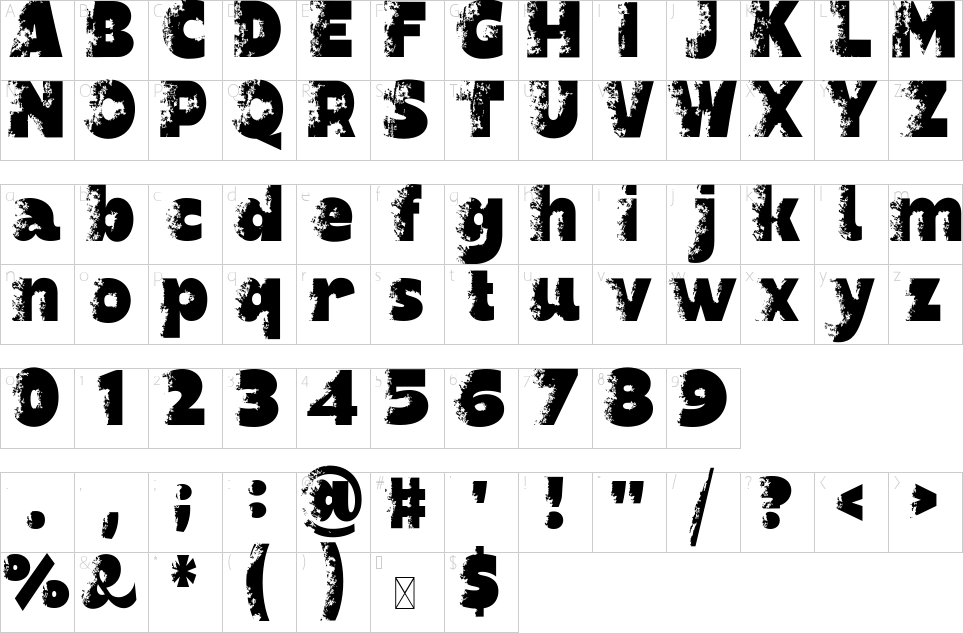
Grunge Font – 1001 Free Fonts – Fonte Grátis
Aqui está uma descrição em português do Brasil, envolvente e natural para a página de download da fonte ‘Grunge Font – 1001 Free Fonts’: Descubra a fonte Grunge disponível gratuitamente e facilmente instalável tanto no Windows quanto no Mac. Com seu design criativo e inovador, a Grunge font se destaca em ambientes onde um estilo arredondado e desorganizado é procurado. O designer 177Studio.com trouxe esta fonte com uma variedade de estilos para enriquecer qualquer projeto visual. Se você está buscando dar um toque único à sua arte digital ou layout web, a Grunge font pode ser a solução perfeita. Sujeitada ao movimento grunge dos anos 90 e suas referências artísticas, esta font oferece um ar de irreverência que certamente vai chamar atenção. Combinando linhas robustas com detalhes suaves e desorganizados, é uma ótima escolha para aqueles que buscam dar ao seu design uma pegada única e autêntica. E melhor ainda: esta fonte está disponível gratuitamente para download em sua versão de 1001 Free Fonts. Se você precisa criar um layout minimalista ou temprece com um estilo mais arrumado, a Grunge font não é apenas útil, ela também oferece uma maneira única de diferenciar seus projetos. Seja para aplicativos móveis ou sites web, a escolha desta fonte pode transformar sua produção em algo que destaca-se do resto da multidão. Portanto, se você está procurando por um pouco de diversidade e criatividade na sua próxima peça gráfica ou projeto de design, o Grunge font tem tudo para torná-lo mais especial.